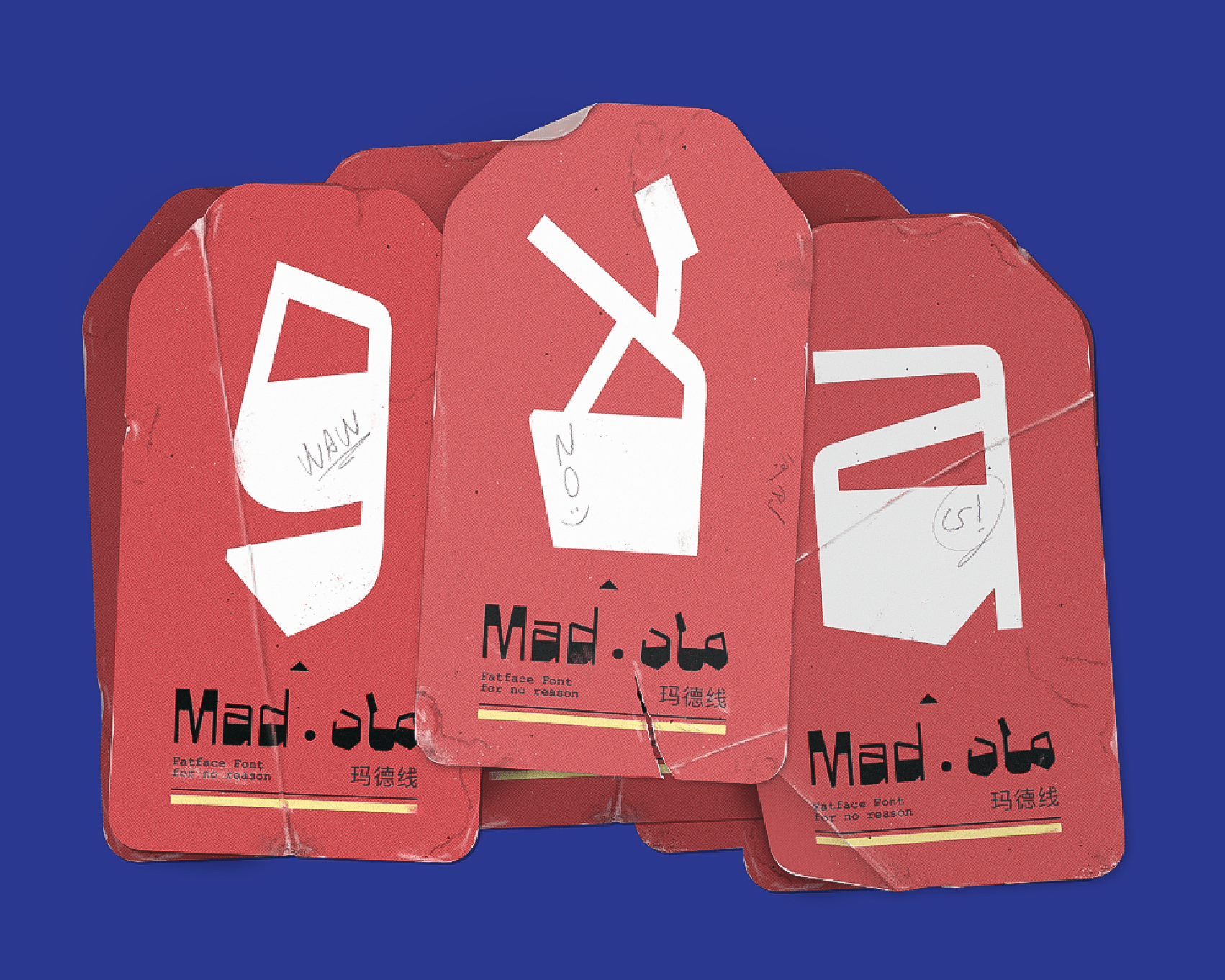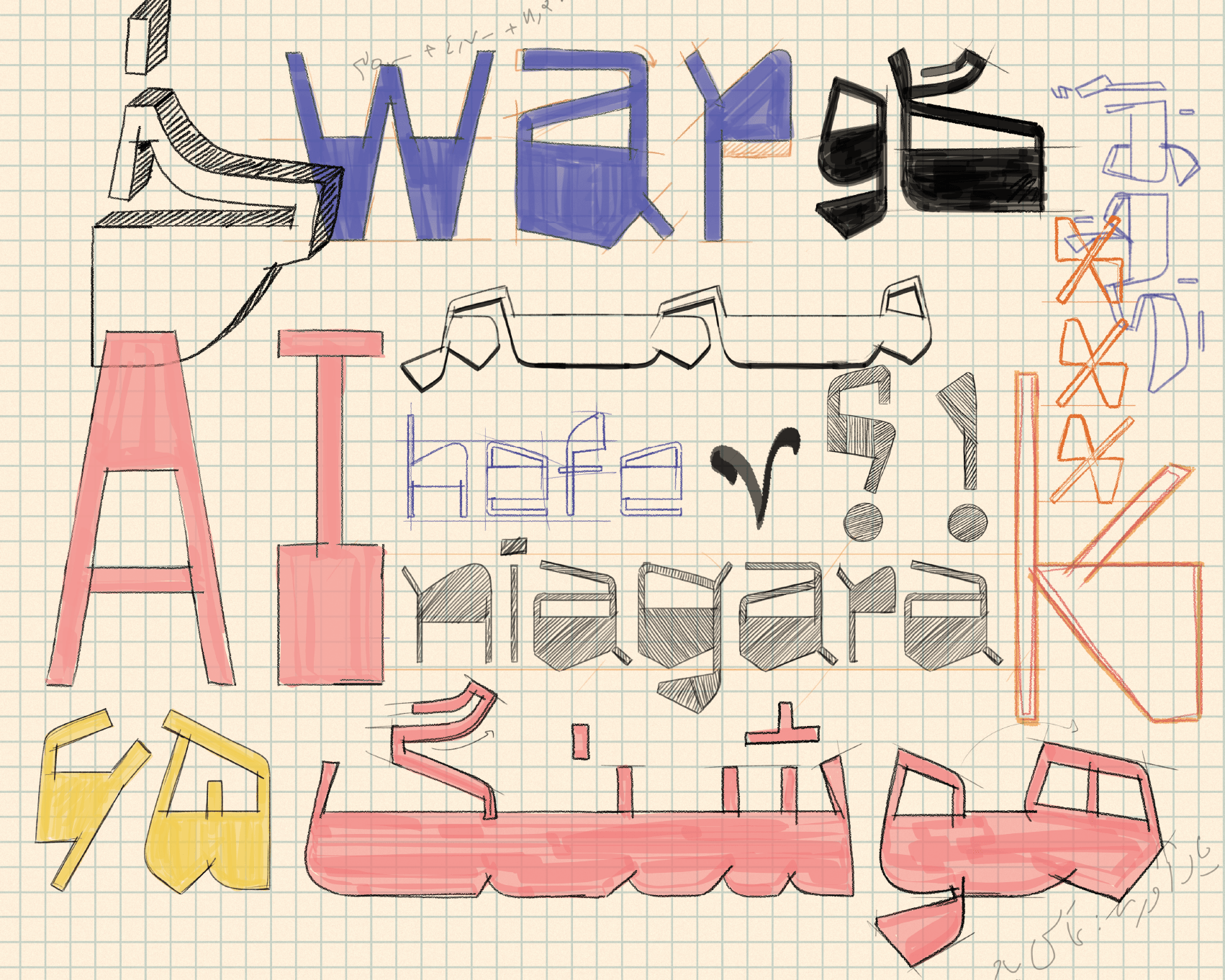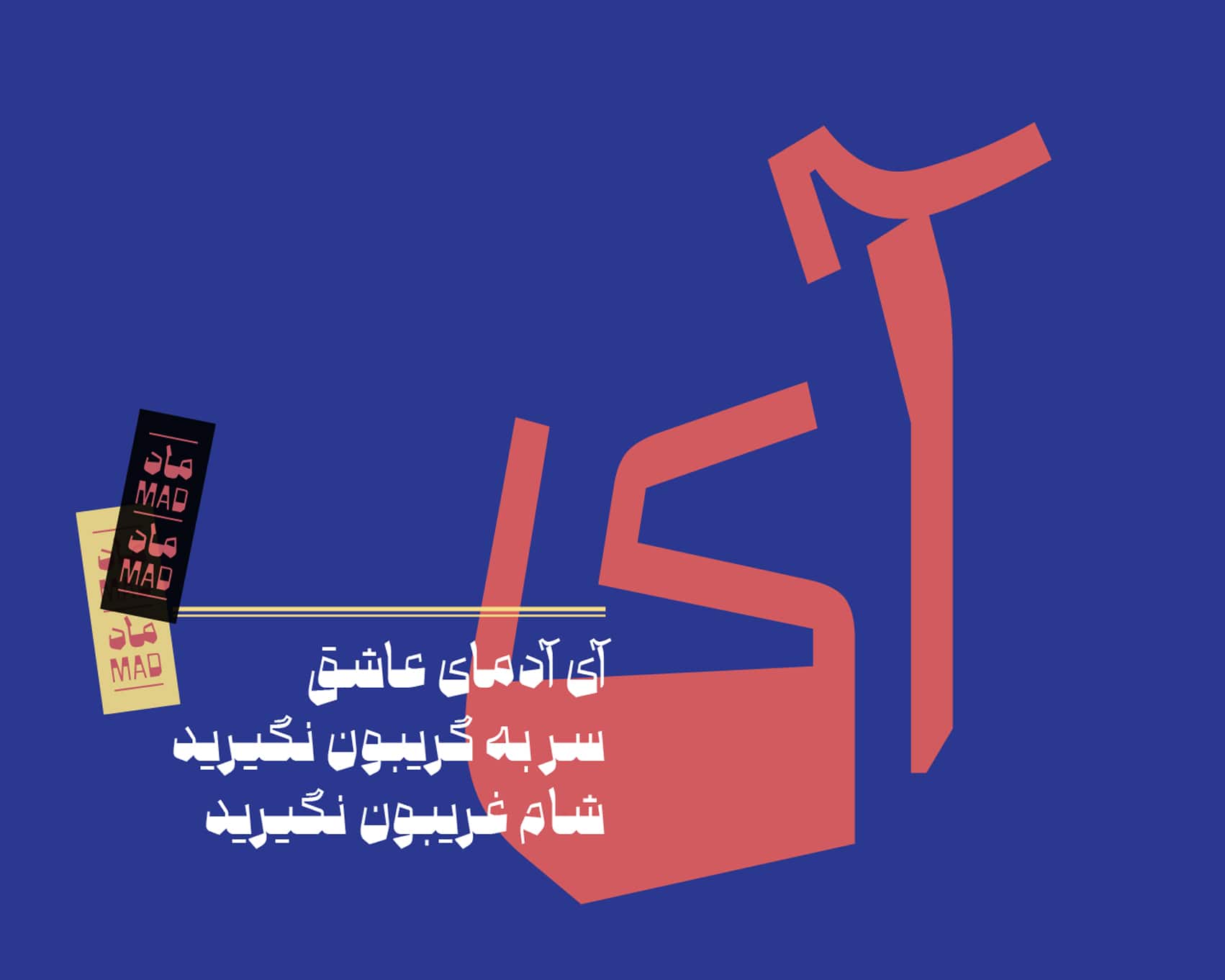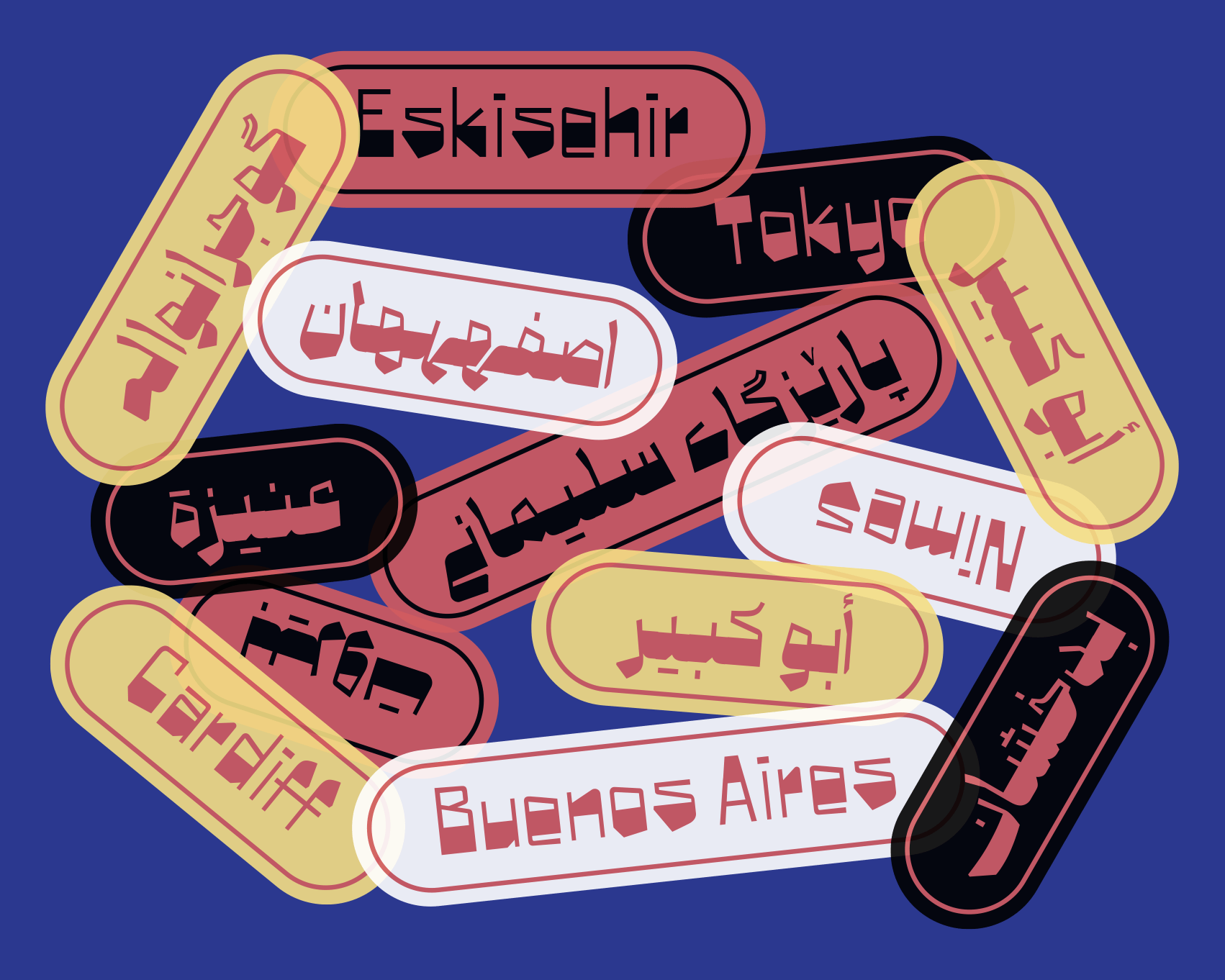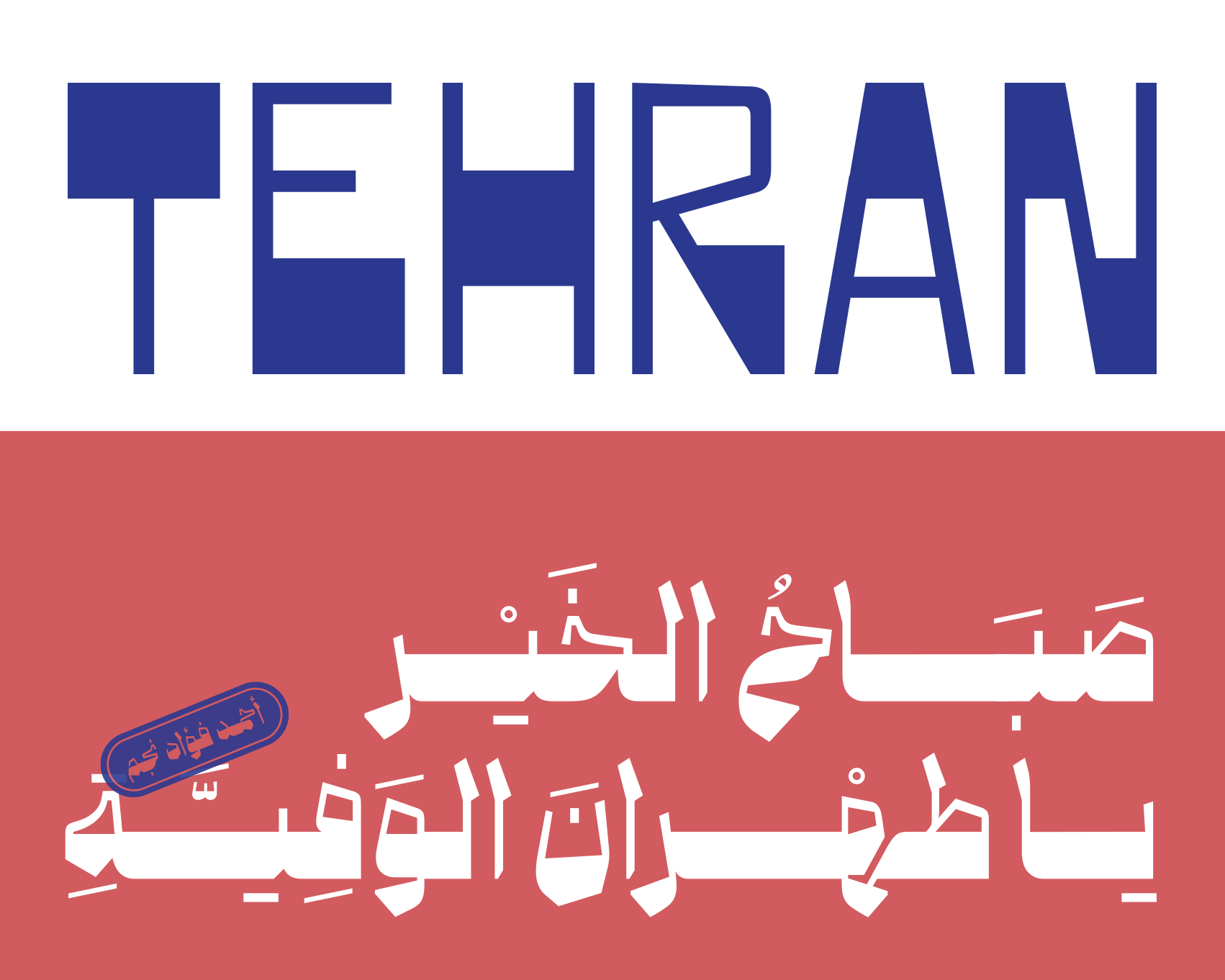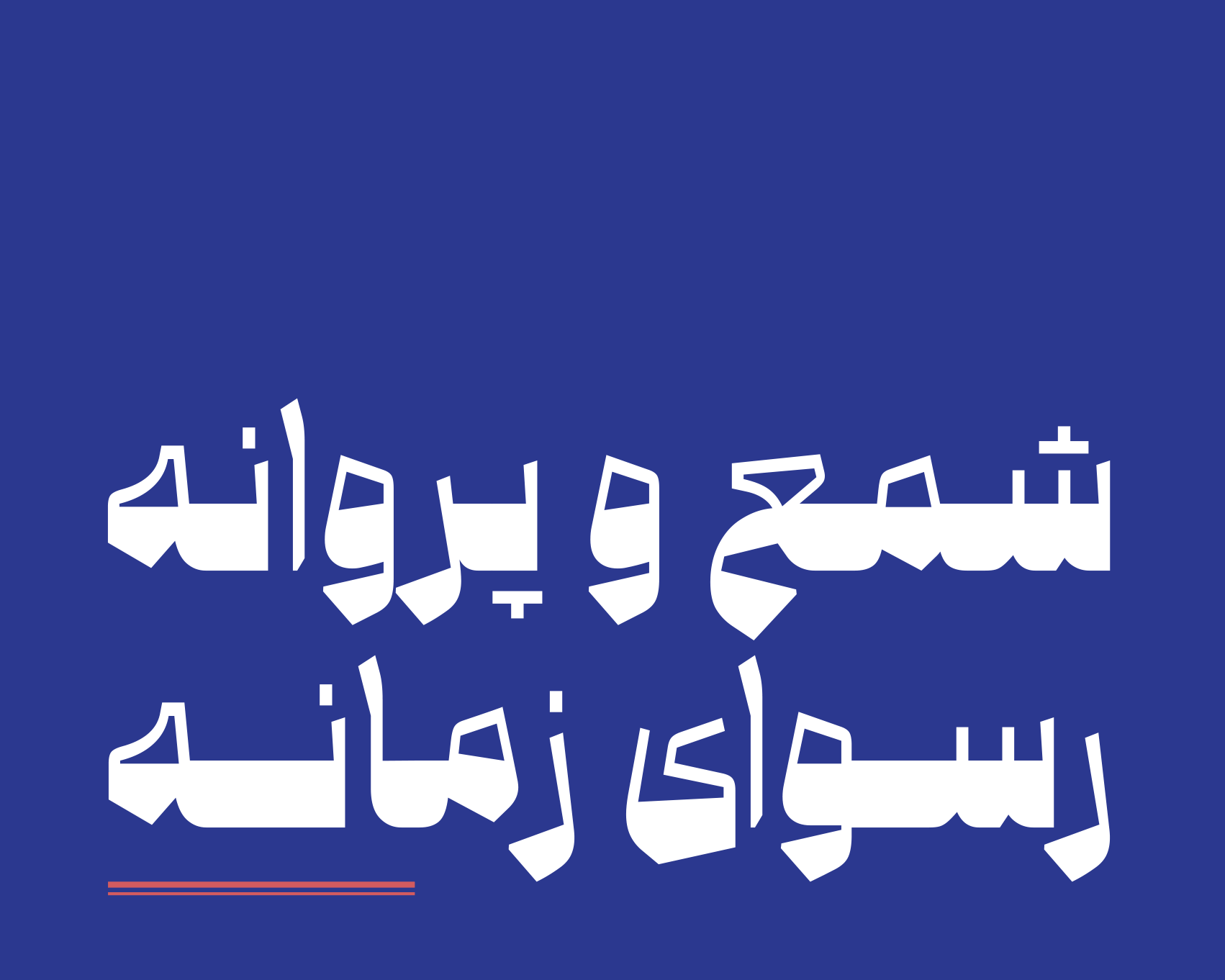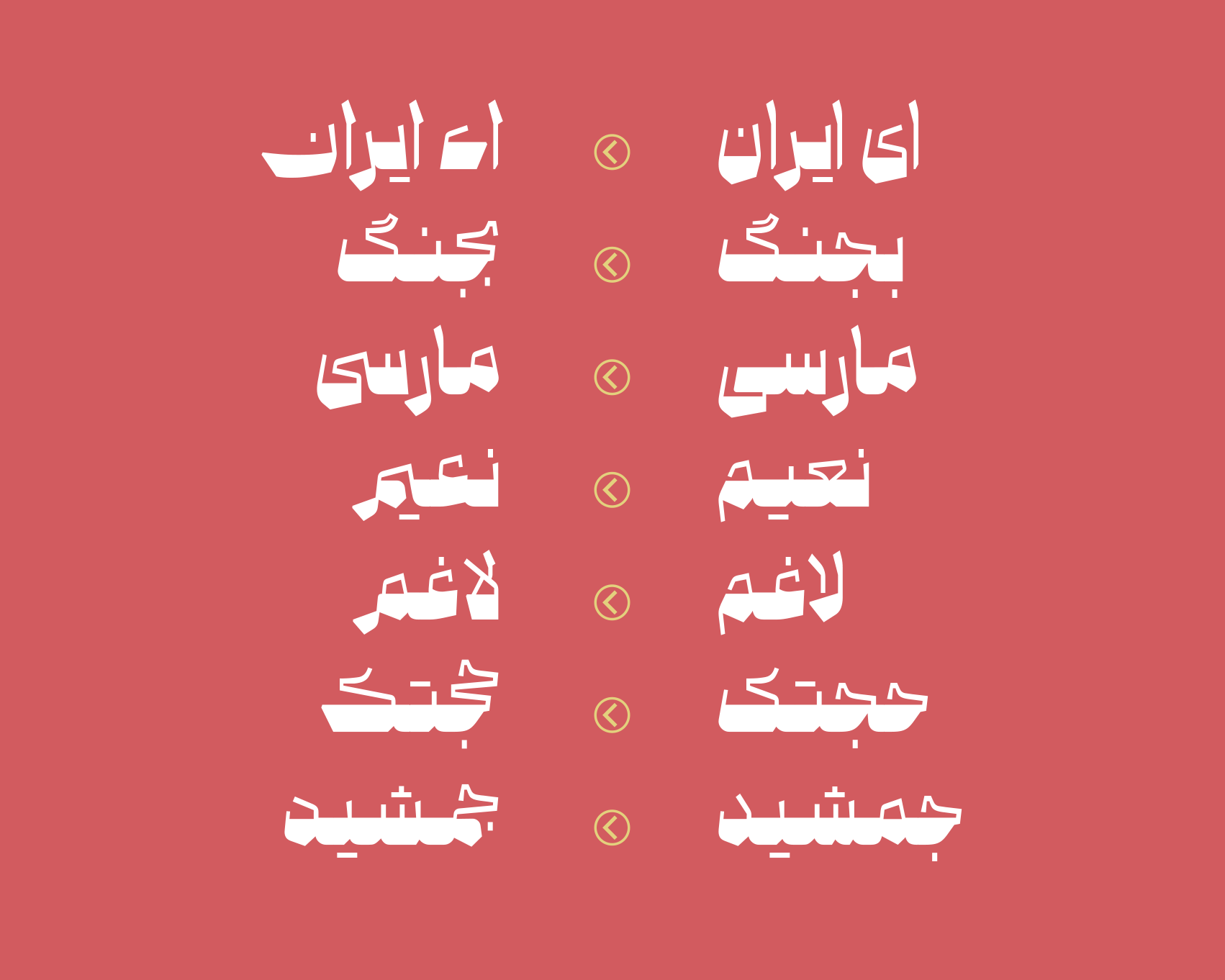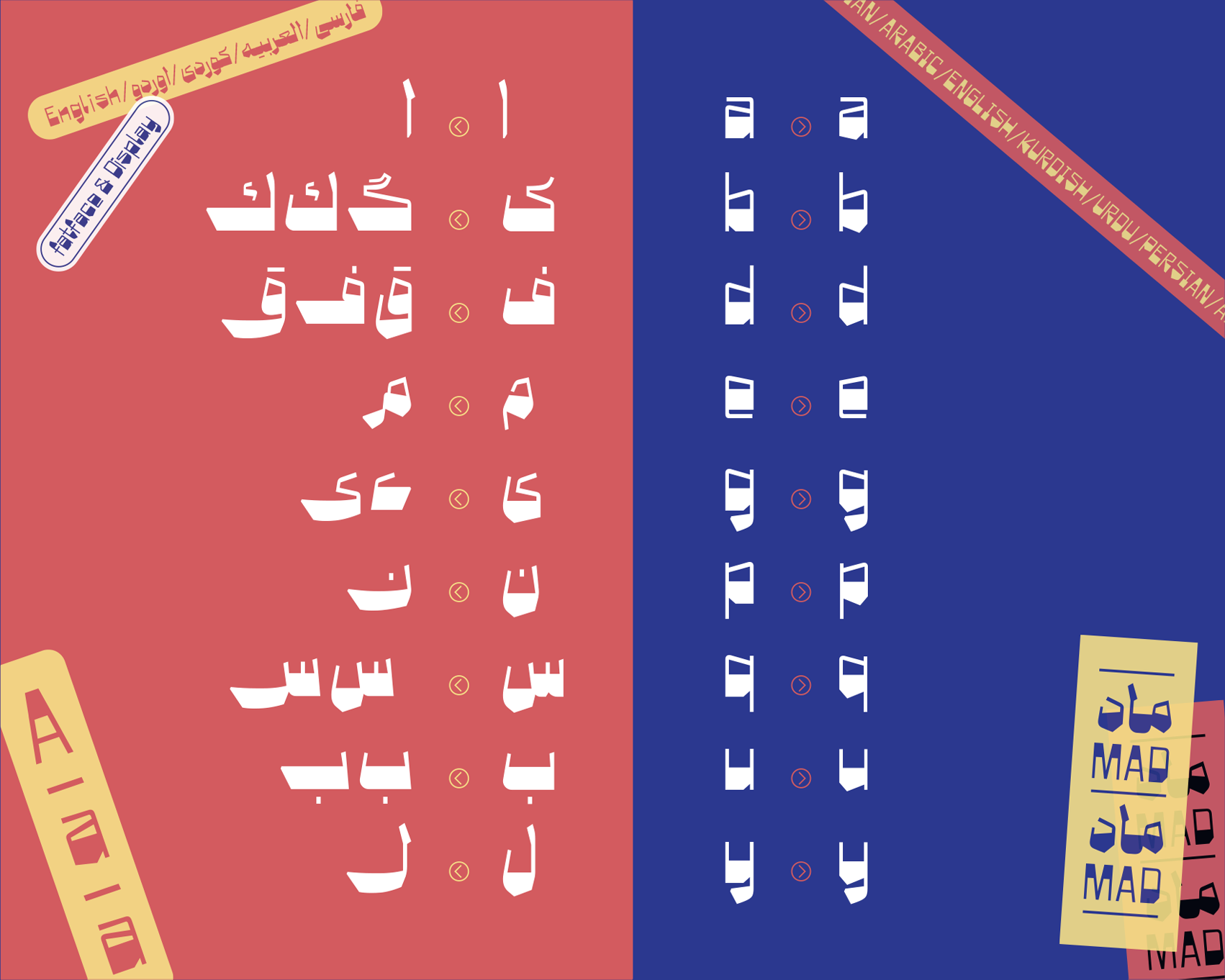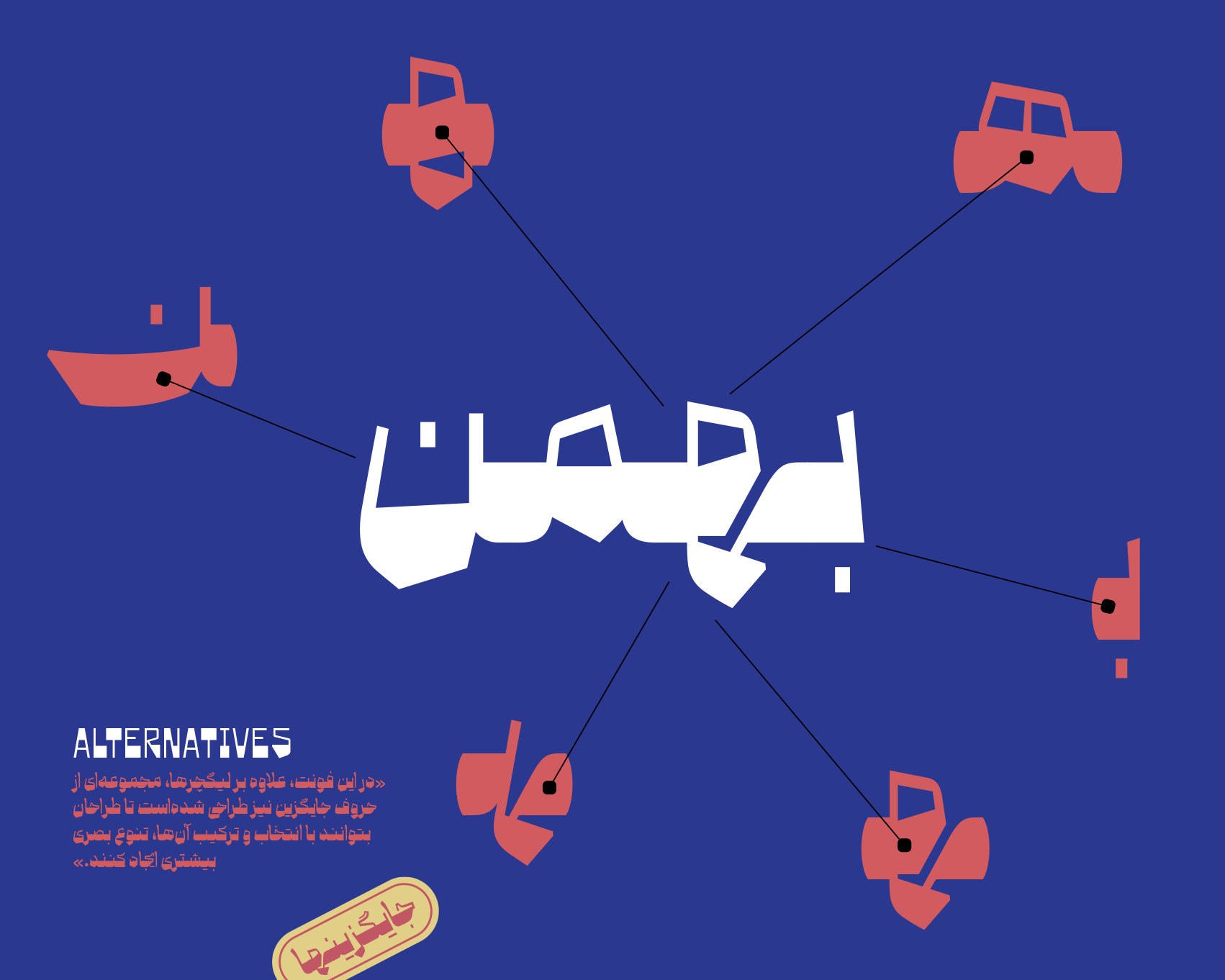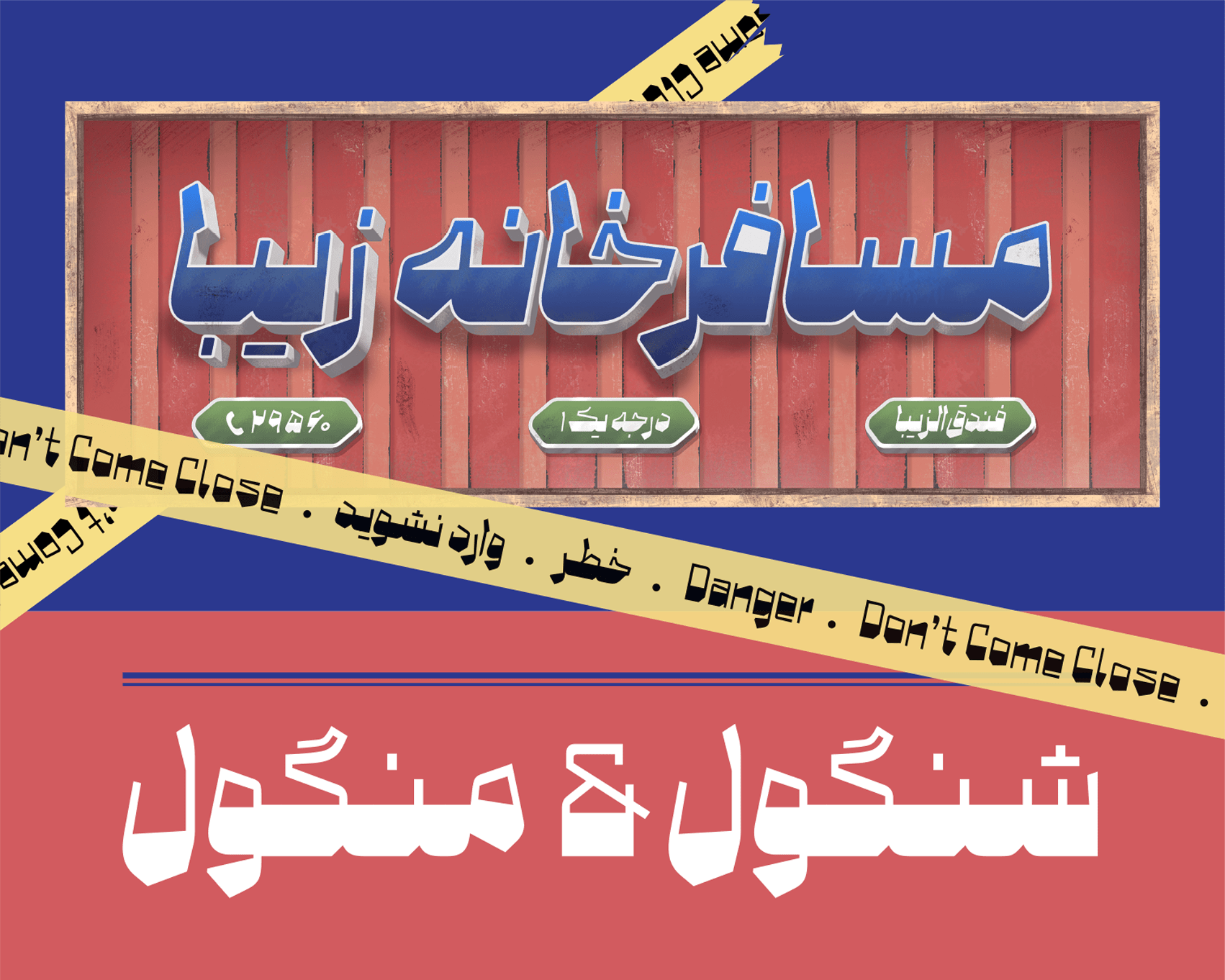
«ماد» حاصل یک تمرین شخصیست (بنا بود شبیه من نباشد!).
با وجود ظاهری شارپ و قدرتمند، این فونت در کاربردهای مختلف انعطافپذیری بالایی دارد و میتواند در موقعیتهای متنوع عملکرد خوبی ارائه دهد.
کنتراست شدید در کنار «چشمهای بزرگ», که نقش مهمی در افزایش خوانایی دارند, باعث میشود «ماد» برای نمایش انواع عناوین و تیترها انتخابی مناسب باشد.
فونت ماد تنها یک وزن دارد، اما بهلطف ترکیبات و کاراکترهای جایگزین متعدد، قابلیتهای کاربردی گستردهای در اختیار طراح قرار میدهد.
فونت ماد از زبانهای فارسی، عربی، کُردی، اردو و انگلیسی پشتیبانی میکند.